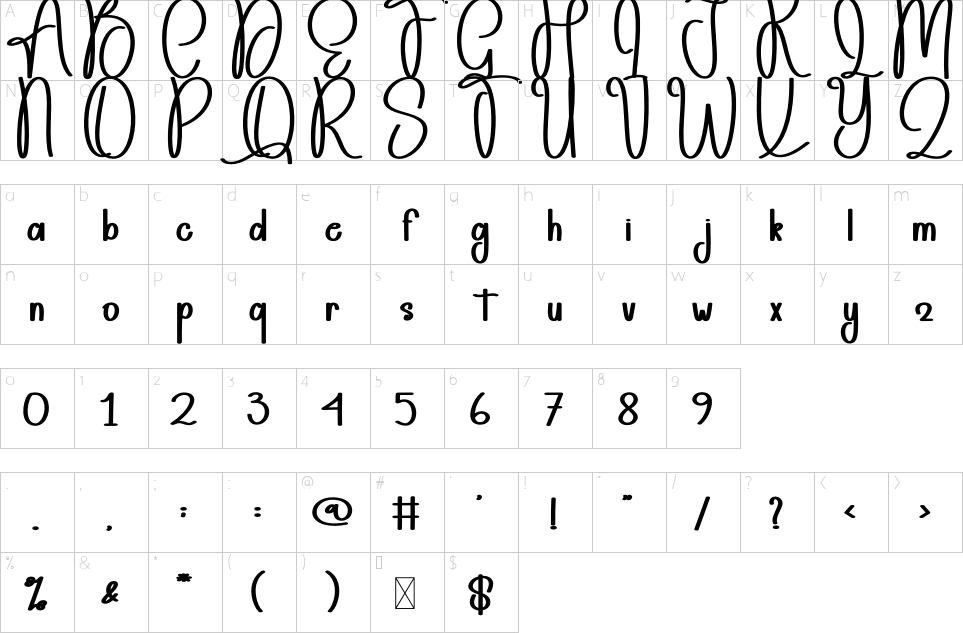
A Milestone Font oferece uma experiência visual única para designers e criadores de conteúdo. Desenvolvida por William Jhordy, esta fonte gráfica se destaca por sua estética elegante e clássica, adequada para diversas aplicações, desde materiais de escritório até editoriais e publicações digitais. Com um design cuidadosamente pensado, a Milestone Font é perfeita para quem busca uma alternativa gráfica atraente para manusear em suas tarefas de design. Com a Milestone Font, você pode adicionar um toque de sofisticação a qualquer projeto, tornando-o mais profissional e atraente. Com 794 downloads, já mostrou seu valor para os designers que buscam um design gráfico moderno e agradável aos olhos. Instale a Milestone Font em seu próximo projeto e veja por si mesmo a diferença que ela pode fazer.